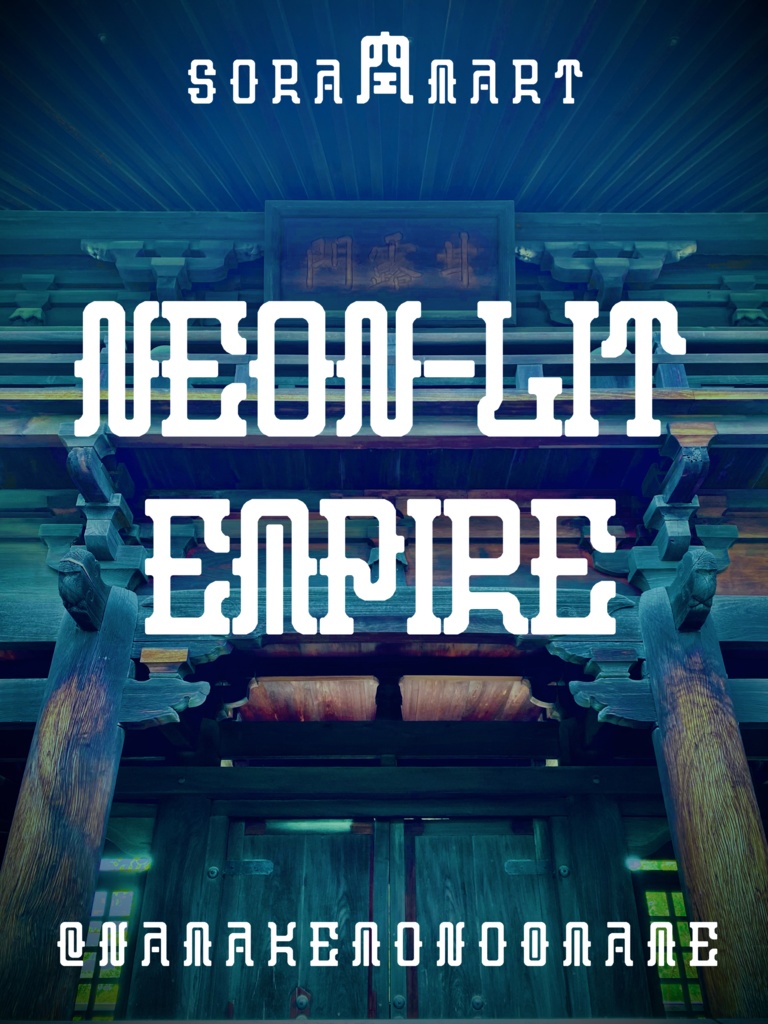
そらマートフォントデータ”Neon-Lit Empire”Digital2,500 JPY加入购物车Buy a GiftAbout Gift”篆書体”をモチーフにしたサイバー調フォント "Neon-Lit Empire" です。 「TrueTypeフォントファイル」という形式です。 ダウンロードした後、Zipファイル内のデータをインストールしてお使いください。 このフォントは商用利用可となっております。 お客様の制作・創作活動のお役に立てれば幸いです。 ※使用上の注意事項などは、添付のReadmeをお読みください。そらマートVisit FANBOX!Fontsフォントデータ”Henge Edge Rock”そらマート2,500 JPYFontsフォントデータ”Henge Edge Tall”そらマート0 JPYFontsフォントデータ”Henge Edge”そらマート0 JPYFontsフォントデータ”Chisel Stroke Wide”そらマート2,500 JPYFontsフォントデータ”Chisel Stroke”そらマート2,500 JPYFontsフォントデータ”Crushed Can Serif Empty”そらマート2,500 JPYFontsフォントデータ”Crushed Can Serif Wide”そらマート2,500 JPYFontsフォントデータ”Crushed Can Serif”そらマート2,500 JPYFontsフォントデータ”Dolce Cube Tall”そらマート2,500 JPYFontsフォントデータ”Dolce Cube”そらマート2,500 JPYFontsフォントデータ”Eight-bit Quest Wide”そらマート2,500 JPYFontsフォントデータ”Eight-bit Quest”そらマート2,500 JPYFontsフォントデータ”Tonik Crate”そらマート2,500 JPYFontsフォントデータ”Vapor Sprout Edge”そらマート2,500 JPYFontsフォントデータ”Vapor Sprout Wide”そらマート2,500 JPYFontsフォントデータ”Vapor Sprout”そらマート2,500 JPYFontsフォントデータ”Star Shoot Ray”そらマート2,500 JPYFontsフォントデータ”Star Shoot Black Wide”そらマート2,500 JPYFontsフォントデータ”Star Shoot Black”そらマート2,500 JPYFontsフォントデータ”Mars Invader Balloon”そらマート2,500 JPY查看更多